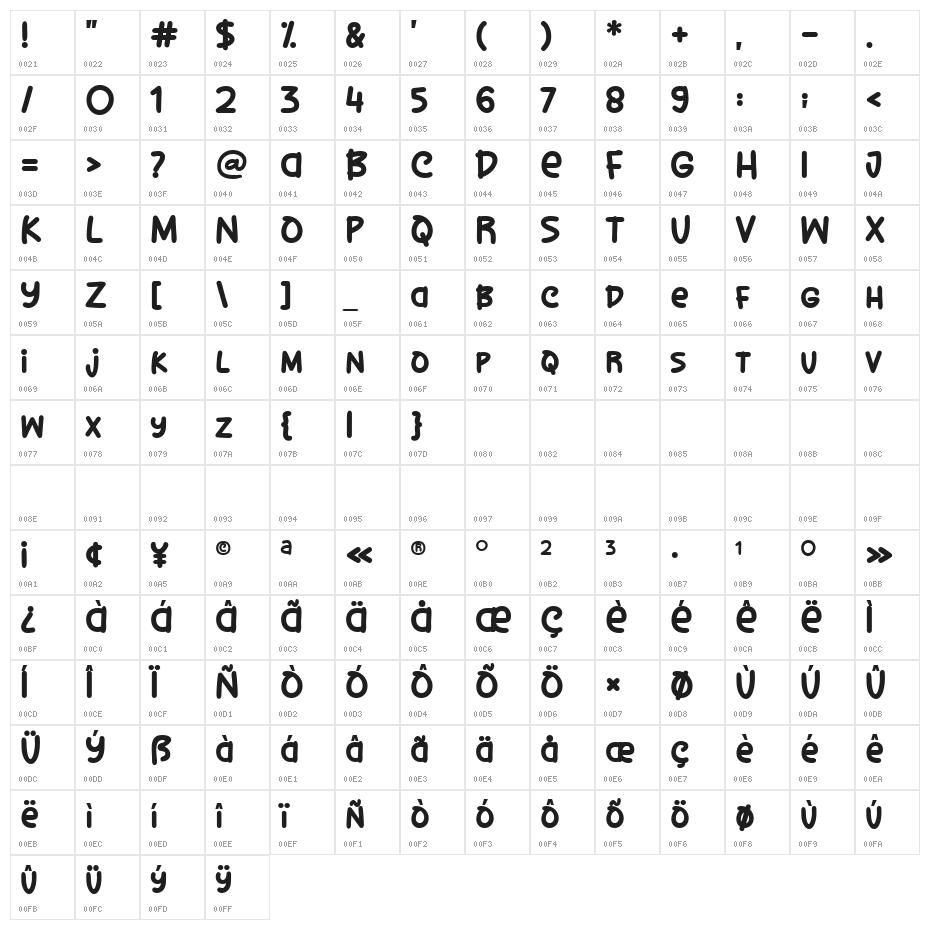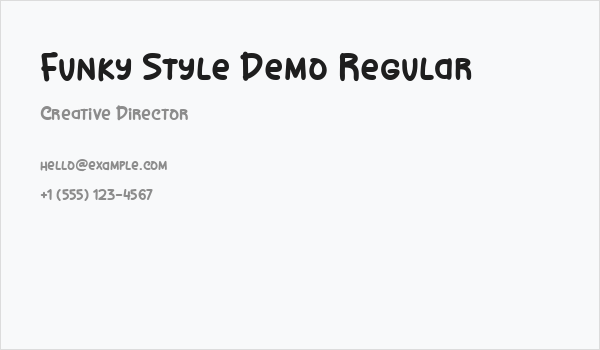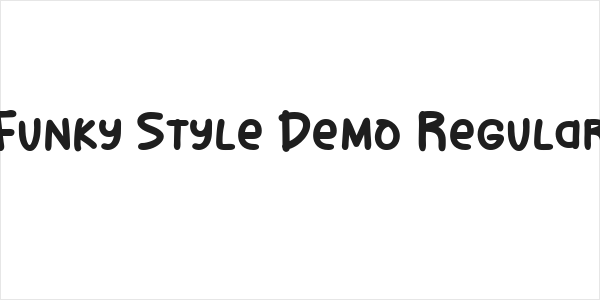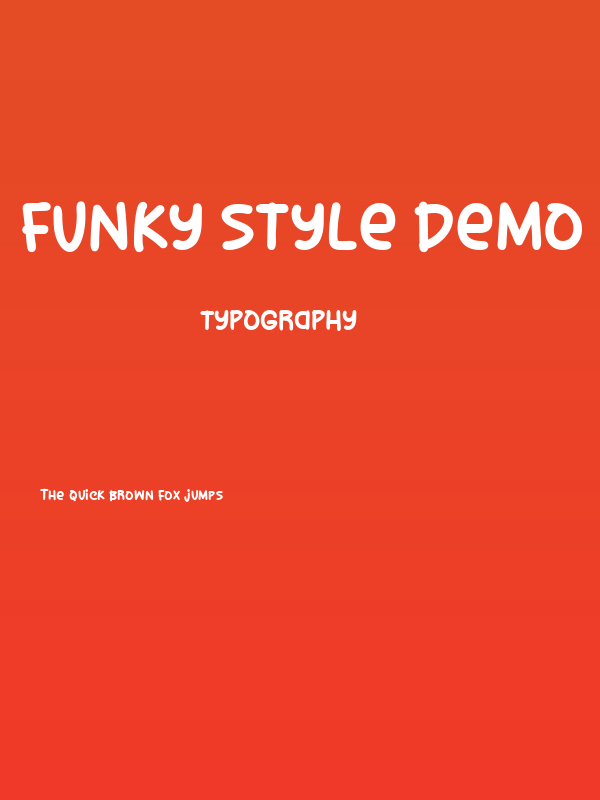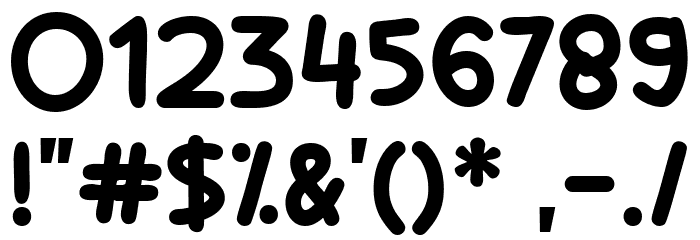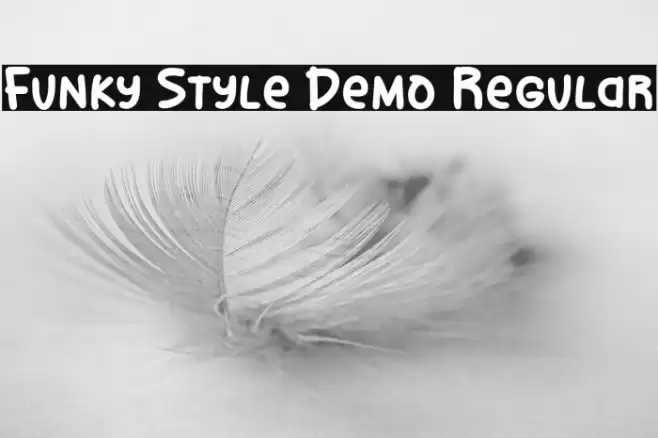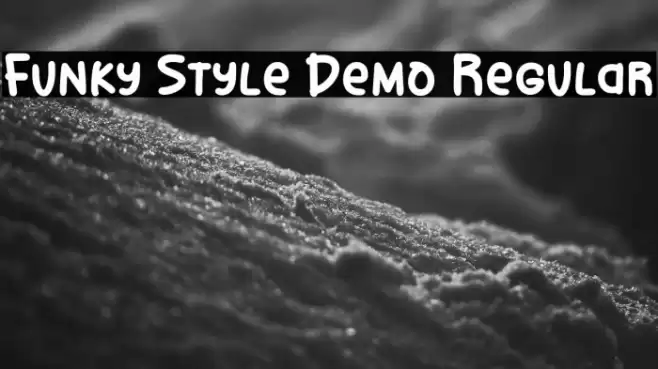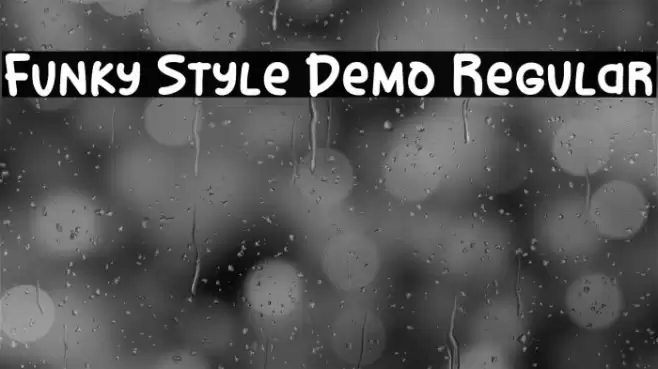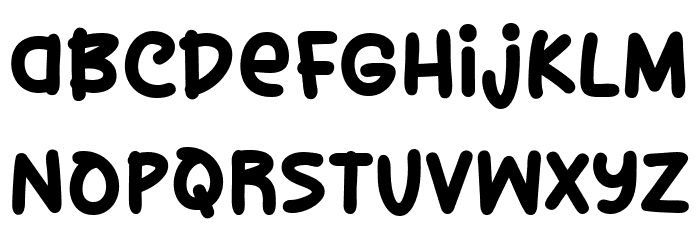
Funky Style Demo Regular Font
| Nome | Funky Style Demo Regular |
| Famiglia di caratteri | Funky Style Demo |
| Stile generale | Playful, Casual, Whimsical |
| Progetti proposti | Ideal for children's books, playful branding, party invitations, and casual posters. |